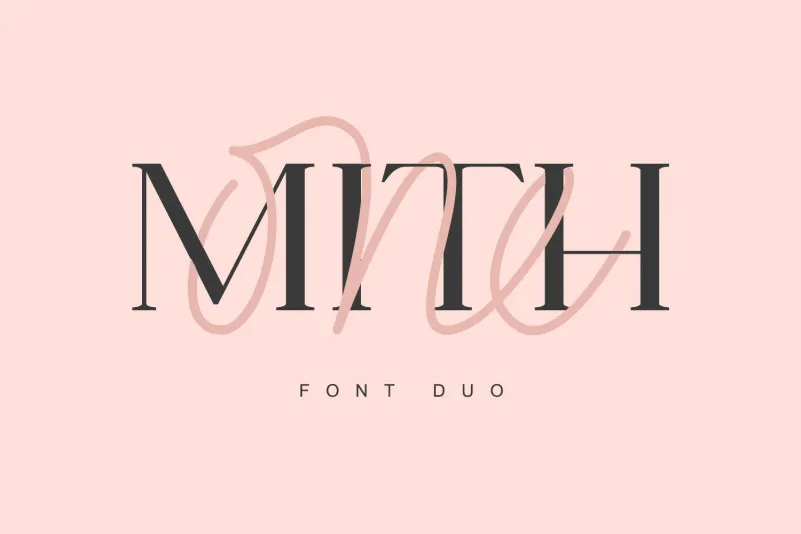
One Mith Font – Download Grátis
A fonte One Mith é perfeita para quem busca algo elegante com uma sensação descontraída. Suas linhas curvilíneas e sua tipografia monoline são um contraponto charmoso à serifada mais sofisticada, criando um ar moderno e sofisticado em qualquer design. Ideal para o dia-a-dia da designer de gráficos ou até mesmo para aqueles que desejam criar mensagens personalizadas com uma autenticidade única. Combine essa fonte com outras elegantes para criar cartões de agradecimento encantadores, designs de papel higiênico incrivelmente bonitos e postes sociais memoráveis. Além disso, ela também é perfeita para o universo das bodas, oferecendo um toque único para seu convite de casamento. Engane-se, você vai adorar essa fonte uma vez que a experimentar.